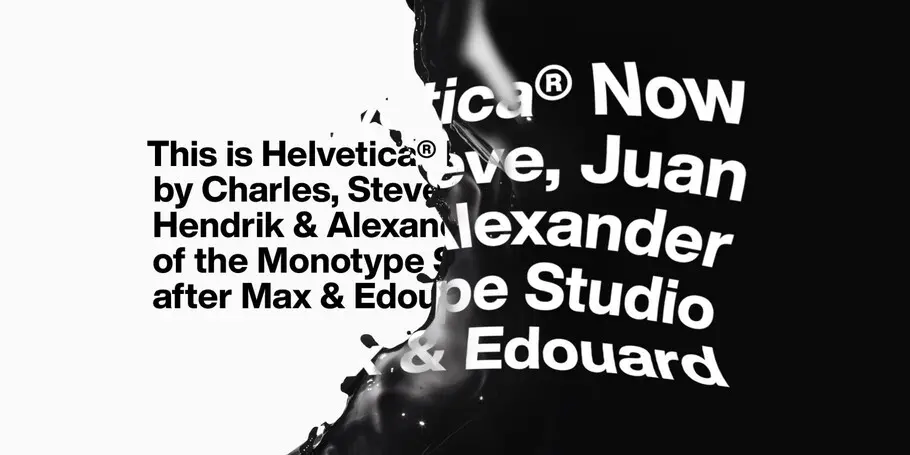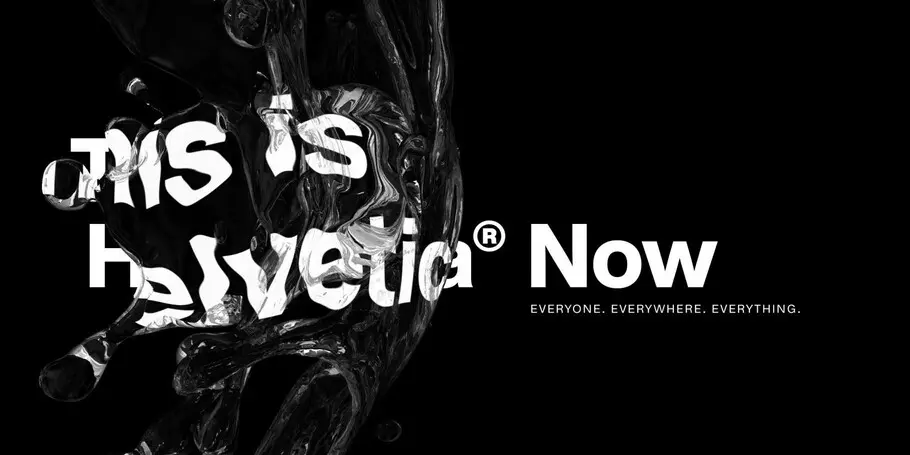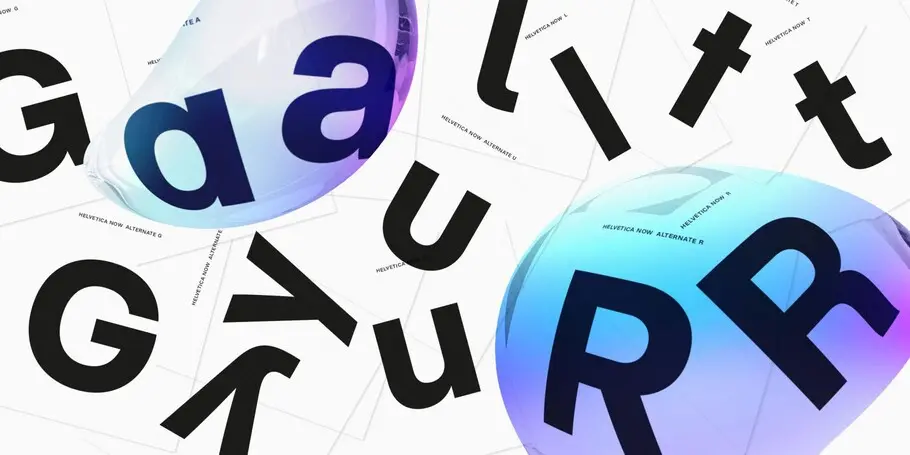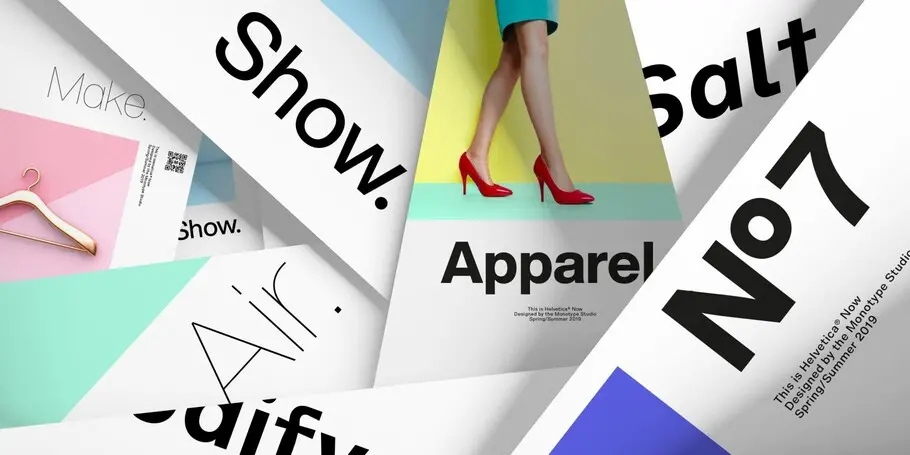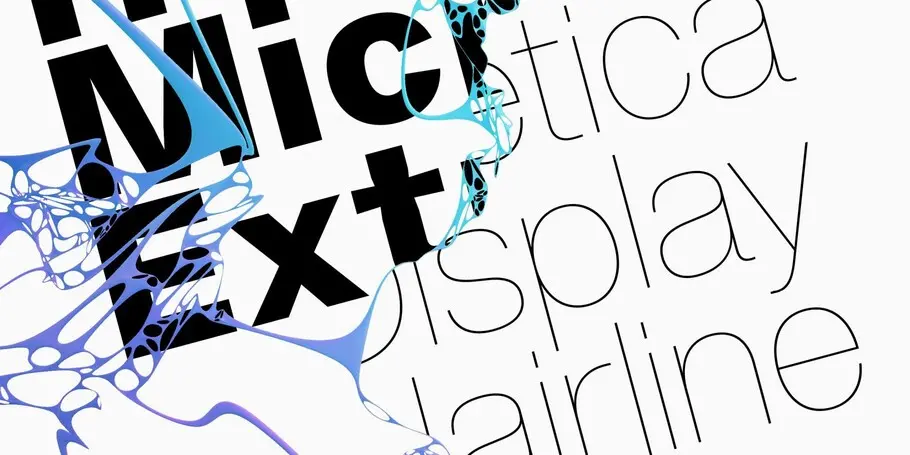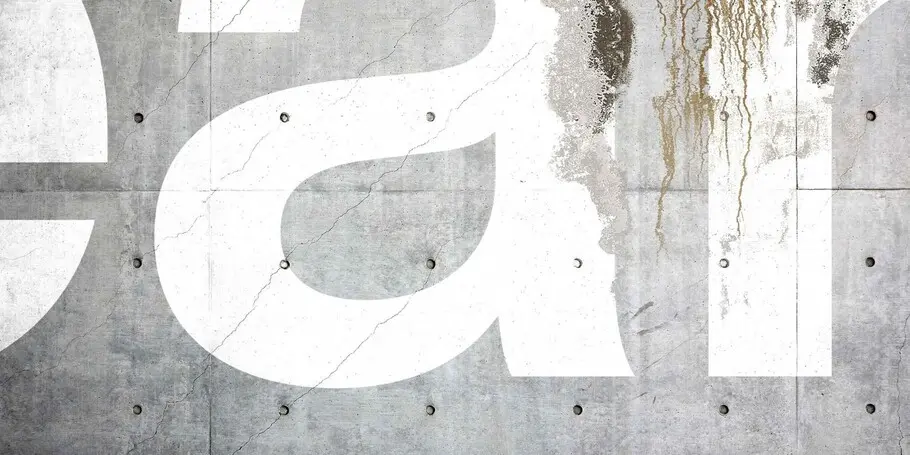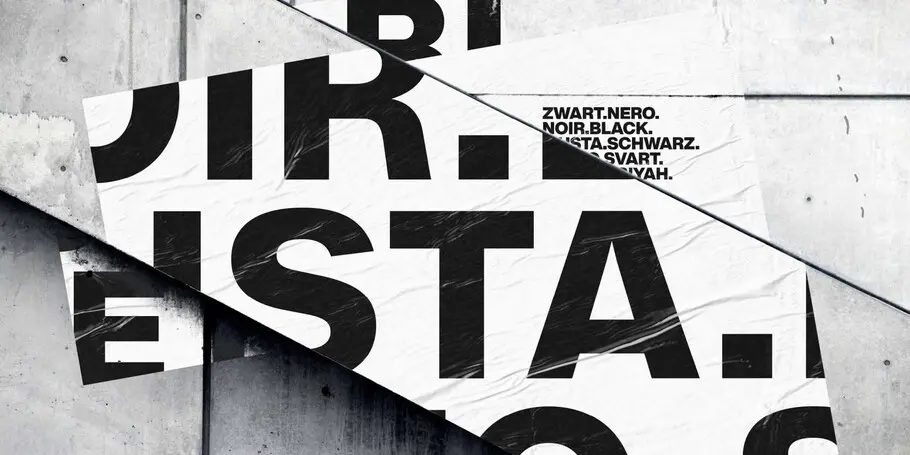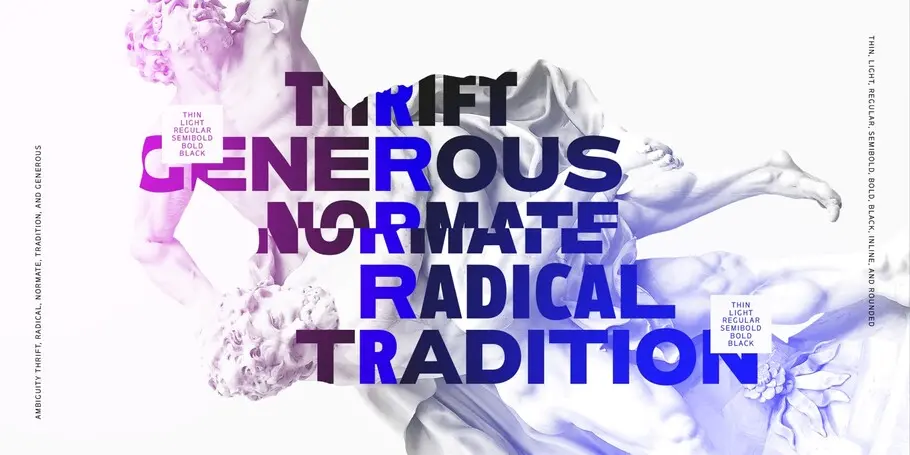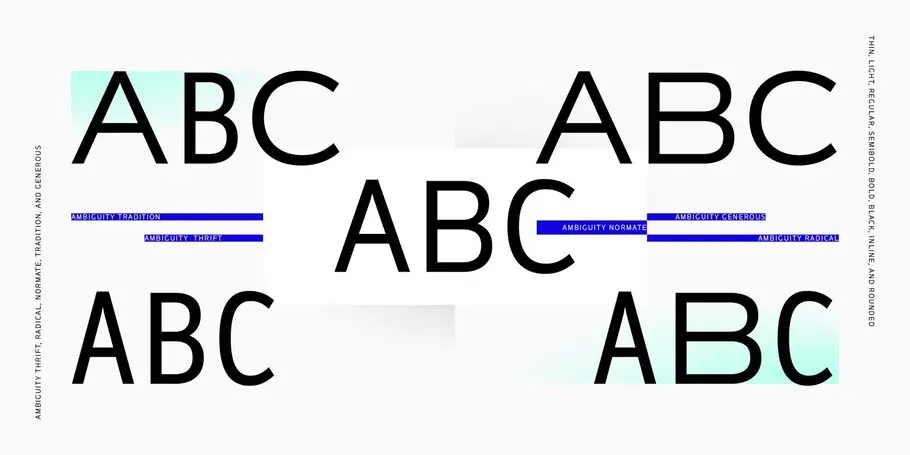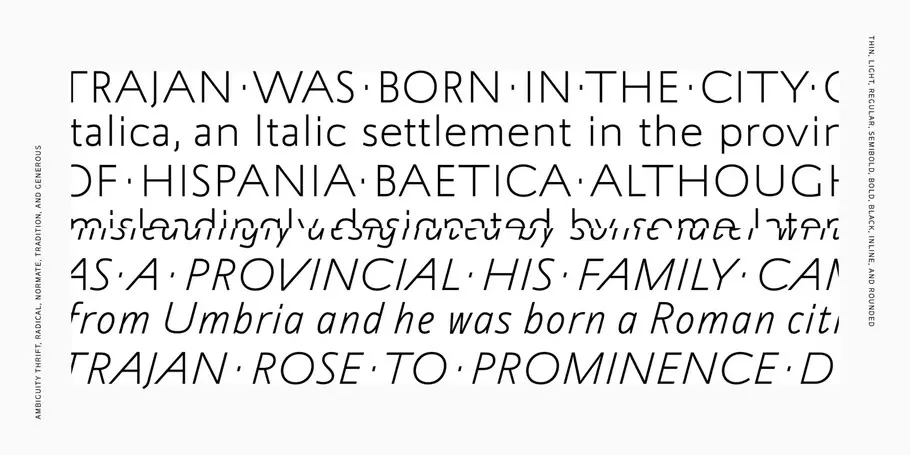
Ambiguity™
观念的交融。选择的多样。
Ambiguity 同时包含传统与激进,以及慷慨与节俭,这鼓励着我们去质疑关于风格与意义交集的信念。Ambiguity 具有五种截然不同的状态:传统、激进、节俭、慷慨和规范,以相反的比例融合了既定概念,创造了一款令人兴奋的工具来调整文本,以及表达从传统到非传统、从节俭到奢侈的一系列态度和信念。
Helvetica Now®
所有人。所有地方。所有事物。
Helvetica® Now也许是有史以来最著名的字体故事的新篇章。Helvetica Now有三种光学尺径可供选择——微型、文本和显示,每个字符都经过重新绘制和整修,并添加了各种有用的变体。
Walbaum
具有优异覆盖范围的回归。
Walbaum系列由Charles Nix、Carl Crossgrove和Juan Villanueva设计,是一款现代的衬线字体设计,可用于从微型说明文本到大标题的各种地方。在其他现代字体倡导朴素的地方,Walbaum则注重热情,使它成为寻求融合了高端风格和亲和力的大型字体系列的品牌的理想之选。